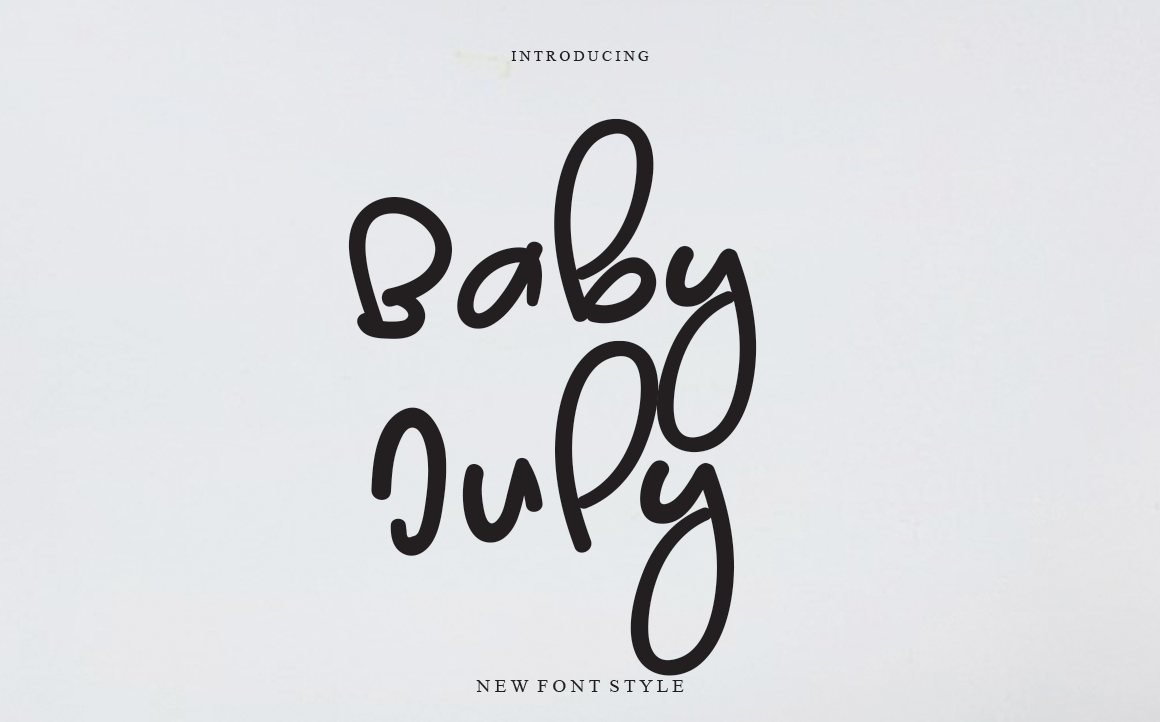
Baby July Font – Download Grátis
A Baby July Font é uma escolha perfeita para quem busca uma fonte script que seja ao mesmo tempo única e descontraída, com um toque ligeiramente desconcertante. Ela combina a simplicidade do estilo de escrita infantil com o encanto da letra cursiva, criando uma combinação irresistivelmente alegre e acessível. Seja para adicionar um toque fresco em seu próximo projeto de redes sociais ou para decorar textos manuscritos em projetos DIY, essa fonte vai transformar qualquer ideia criativa num verdadeiro trabalho de arte. Perfecta para quem procura uma fonte que brinca com os limites da tipografia, a Baby July Font é perfeita para designers e aficionados por gráficos buscando um toque amigável e divertido em seus projetos.